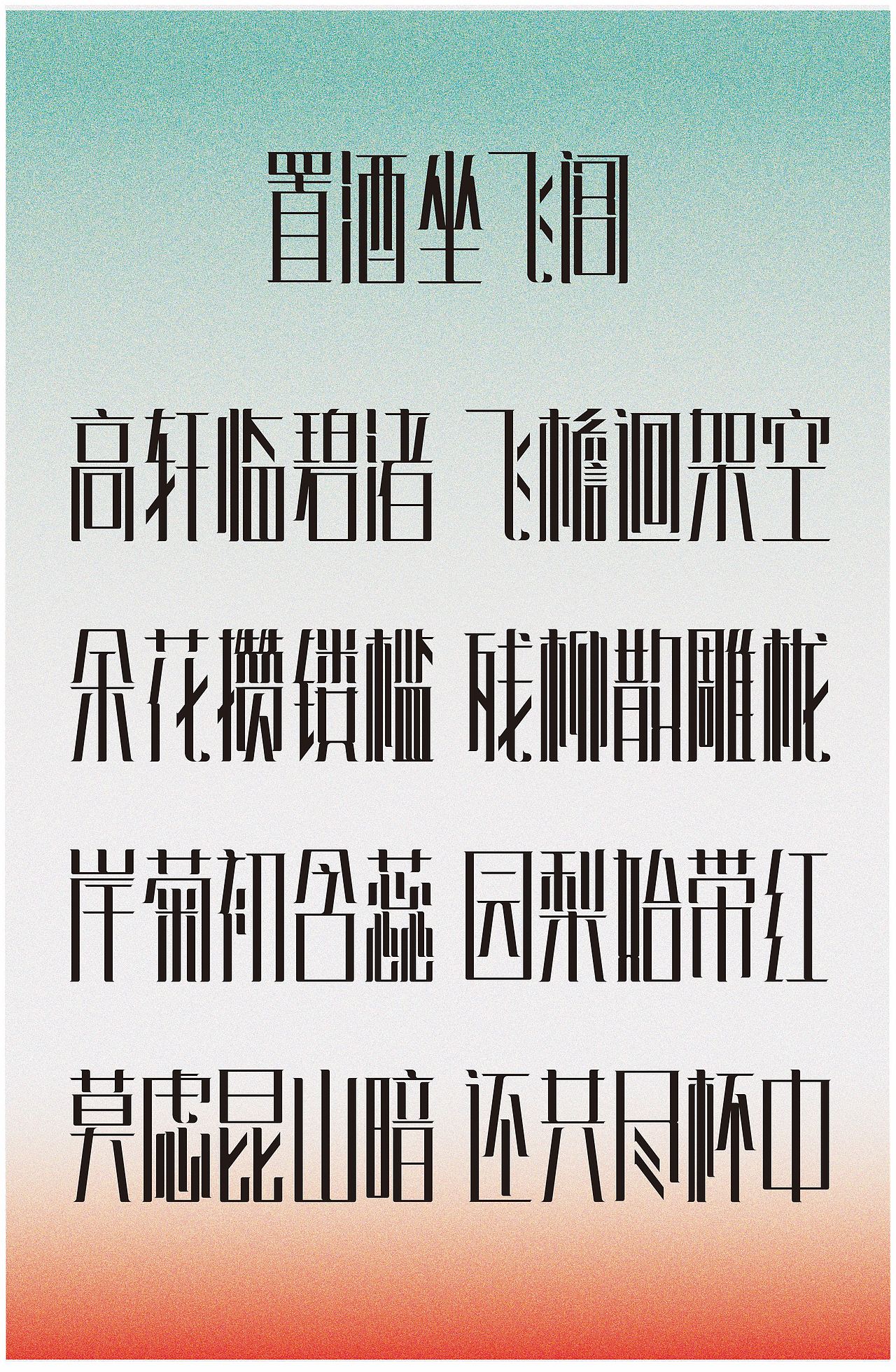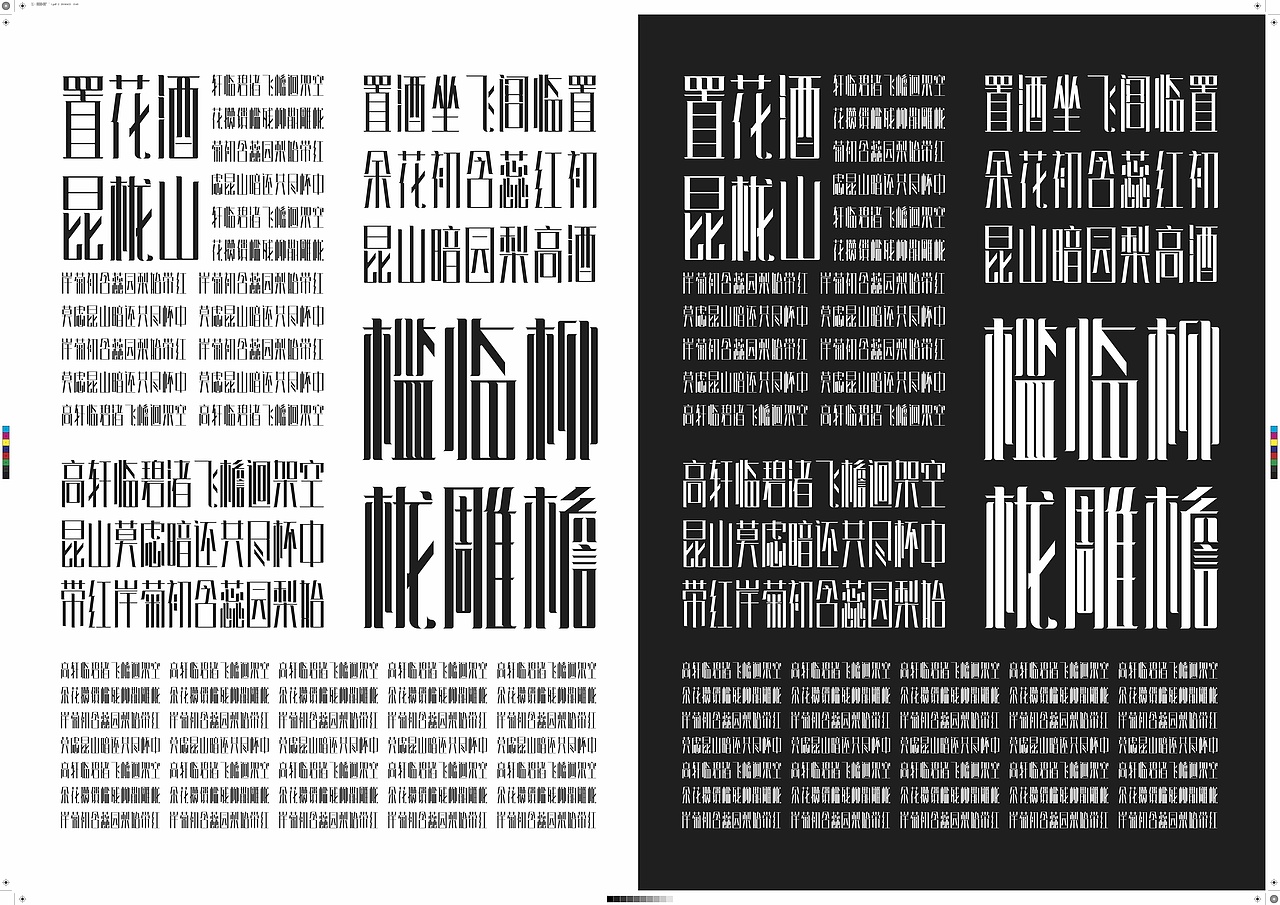
小飞檐体字体设计
飞檐体:飞檐,汉族传统建筑檐部形式,多指屋檐特别是屋角的檐部向上翘起,若飞举之势,常用在亭、台、楼、阁、宫殿、庙宇等建筑的屋顶转角处,四角翘伸,形如飞鸟展翅,轻盈活泼,所以也常被称为飞檐翘角。飞檐翘角的这种托举之势不仅给建筑增添了一种升腾感也营造出一种壮观的民族气势,所以想借助此形与字体设计结合来创作。
如图17,此款字体修长、见解,突出了利郎、雅致、偏文气的气质,但感觉上少了点印象中中国大型古建筑的恢弘气势,更像是亭台楼阁的气质,比较文气,所以进行改进、在设计。